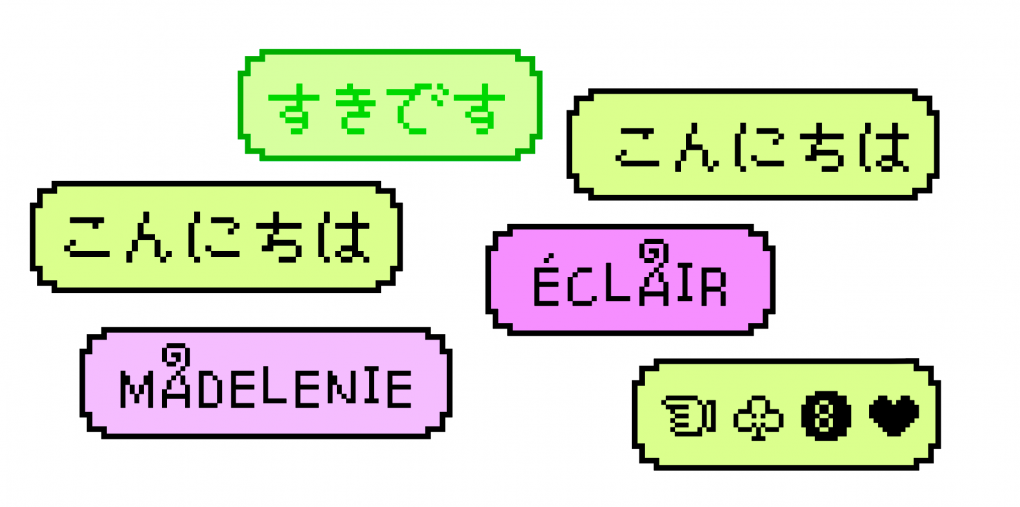
작은 네모 블록으로 표현된 폰트, 픽셀 폰트 시리즈
픽셀 폰트(a.k.a 비트맵 폰트)가 뭐예요?
픽셀 폰트는 크게 확대했을 때, 마치 정사각형 블록을 쌓은 듯한 형태를 지닌 폰트입니다. 표현은 제한적이지만 디지털 화면, 특히 해상도가 낮은 화면에서 명료하게 표현할 수 있다는 강점이 있어요. 버스 정류장의 전광판과 같은 곳에서 자주 활용되며, 추억의 비디오 게임, 콘솔 게임의 저해상도 그래픽 등에서도 픽셀 폰트를 만나볼 수 있어요. 픽셀 폰트는 식을 줄 모르는 뉴트로, Y2K의 유행과 함께 여러 분야에 걸쳐 소환되고 있습니다.
새롭게 찾아온 산돌 픽셀 시리즈✨
「SD 픽셀」 시리즈는 2000년대 초반 웹폰트로 처음 공개되었던, 산돌의 픽셀 폰트를 복원해 가공한 폰트 시리즈입니다. 산돌의 모바일 폰트 브랜드인 ‘Iam’에서 먼저 공개된 「SD 픽셀쪽지」와 「SD 픽셀비밀쪽지」, 그리고 「SD 픽셀굿모닝」, 「SD 픽셀굿밤」, 「SD 픽셀동동동」, 「SD 픽셀쁘띠공주」, 「SD 픽셀사과나무」, 「SD 픽셀섬섬」, 「SD 픽셀요술지팡이」, 「SD 픽셀종이학」까지 총 10종으로 출시했습니다.
2000년대 초반의 픽셀 폰트와 2023년의 픽셀 폰트, 무엇이 달라졌나요?
2000년대 초반에는 웹 환경에서 빠르게 표현이 되어야 했을 거예요. 그러려면 폰트의 용량이 작을수록 좋고요. 폰트 파일의 용량을 낮추는 쉽고 효과적인 방법은 글자 수를 줄이는 것입니다. 그래서 당시 픽셀 폰트는 한글 2,350자만 지원했습니다.
2023년 지금, 다시 선보이는 「SD 픽셀」 시리즈는 더 자유로운 표현을 할 수 있도록 11,172자의 한글을 모두 제작했습니다. 덕분에 카카오톡 등 모바일 메신저에서 사용하기에 적합합니다. 그리고 다양한 기호와 부호들을 추가로 제작했는데요, 시리즈 중 「SD 픽셀쪽지」, 「SD 픽셀비밀쪽지」, 「SD 픽셀동동동」, 「SD 픽셀섬섬」은 라틴 확장도 지원하고 있어 다이어크리틱*이 포함된 문자도 소화할 수 있다고 하네요.
🖋다이어크리틱 : 글자의 위나 아래에 찍어 기존의 철자와는 다른 발음이나 의미를 부여하는 기호